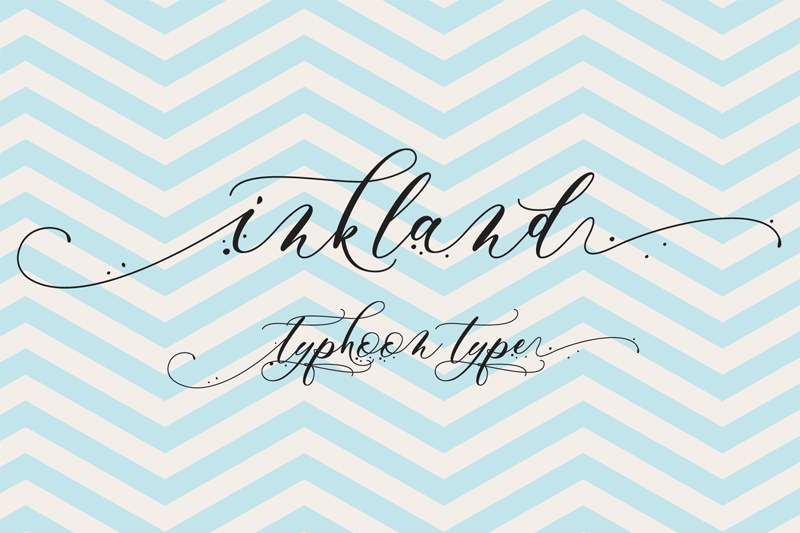
Inkland Script Font – Download Grátis
A Inkland é uma nova adição à família das fóntes digitais que imediatamente te transporta para o mundo do estilo autêntico e delicado da escrita a mão. Desenvolvida pelo designer Suthi Srisopha da Typhoon Type, essa fonte vem revolucionar as propostas de design em seus diferentes aspectos. Inkland não apenas traz à tona um estilo decorativo e elegante que remete diretamente à letra escrita a mão, mas também oferece uma experiência única para projetistas gráficos. Perfeita tanto para criar cartões de aniversário com um toque único, como para dar identidade à sua marca através de materiais de embalagem ou para personalizar arte e selos, Inkland é o ideal para quem procura algo que fique ainda mais marcante em suas criações. Como fonte decorativa, ela oferece uma diversidade de opções que vão desde texturas suaves até traços rústicos, todas criadas a partir do amor pela arte da escrita a mão. Inkland está disponível tanto para uso pessoal quanto para projetos comerciais, permitindo-lhe explorar suas potenciais infinitas e criar design de qualidade. Com Inkland na sua coleção de fóntes digitais, você terá um recurso que não apenas se destaca em qualquer projeto, mas também reflete a riqueza do processo criativo da arte da escrita a mão.